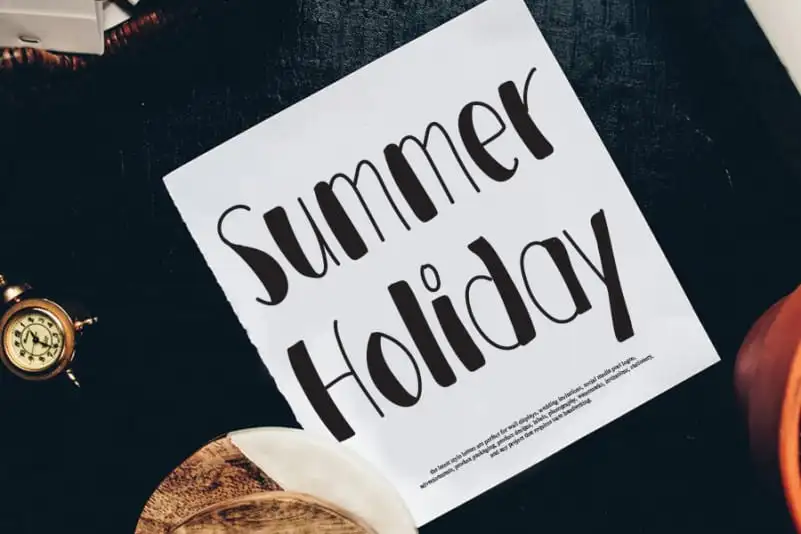
A Summer Holiday Script Font é uma elegante e fresca fórmula de escrita a mão. Criada pelo designer andikastudio, ela mantém influências clássicas do calligrafia enquanto permanece moderna e atual. Se você está procurando por um estilo que seja tanto uma paixão quanto um instrumento para seus projetos, esta fonte é certamente sua escolha perfeita. Experimentar Summer Holiday Script Font é garantir que seu projeto atingirá o topo de eficácia e sofisticação.